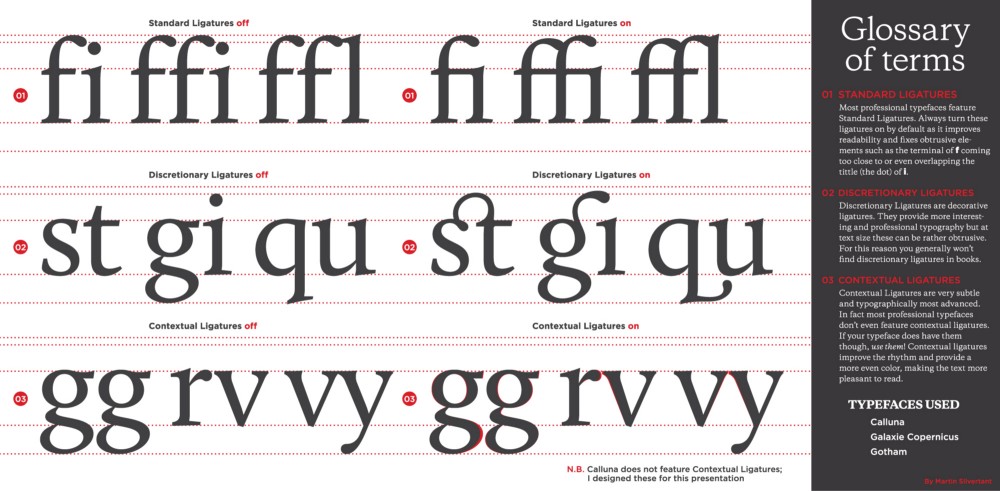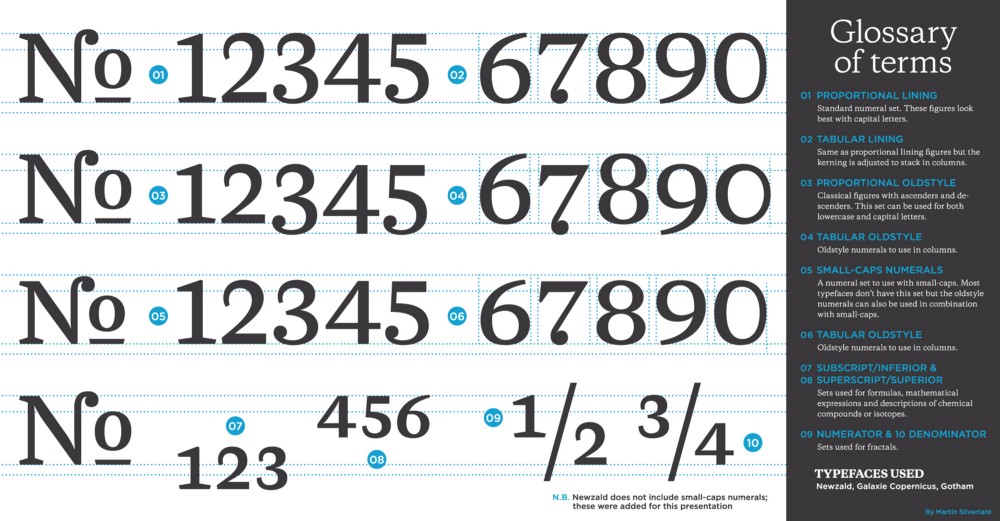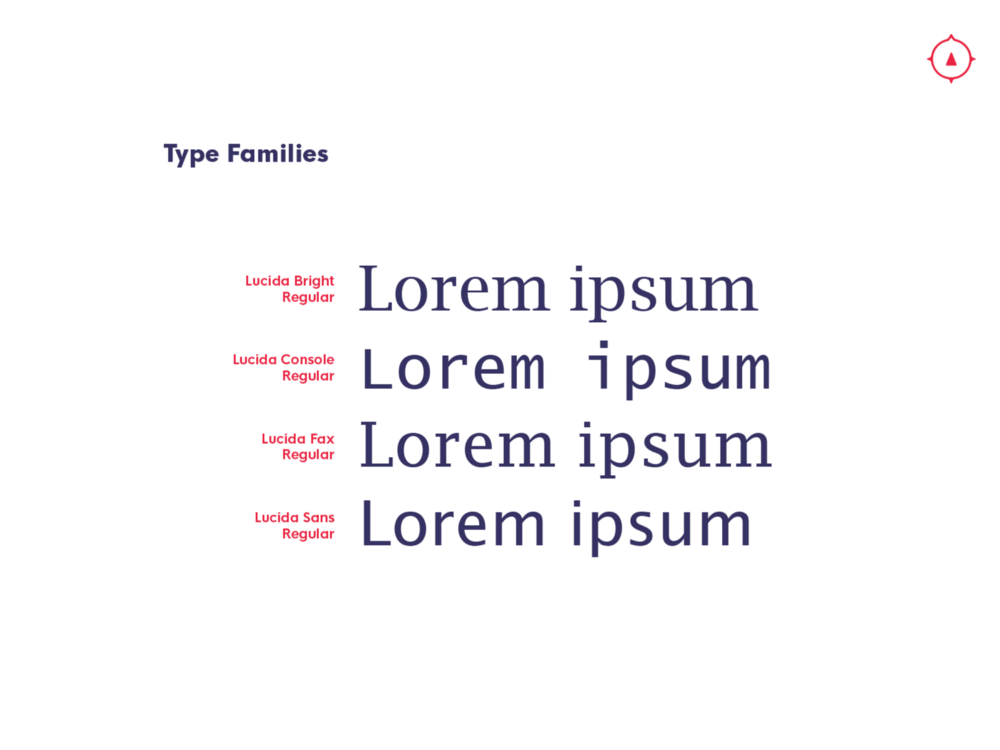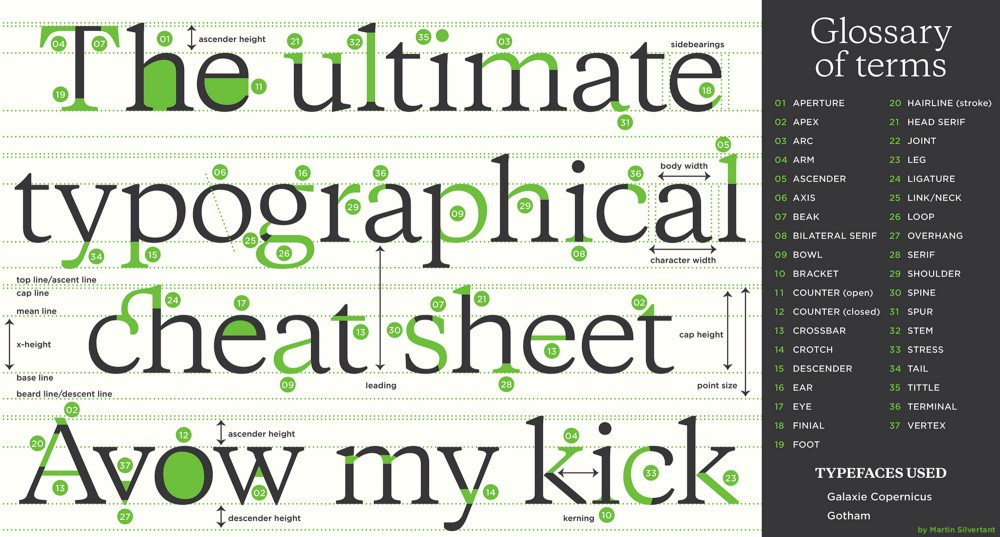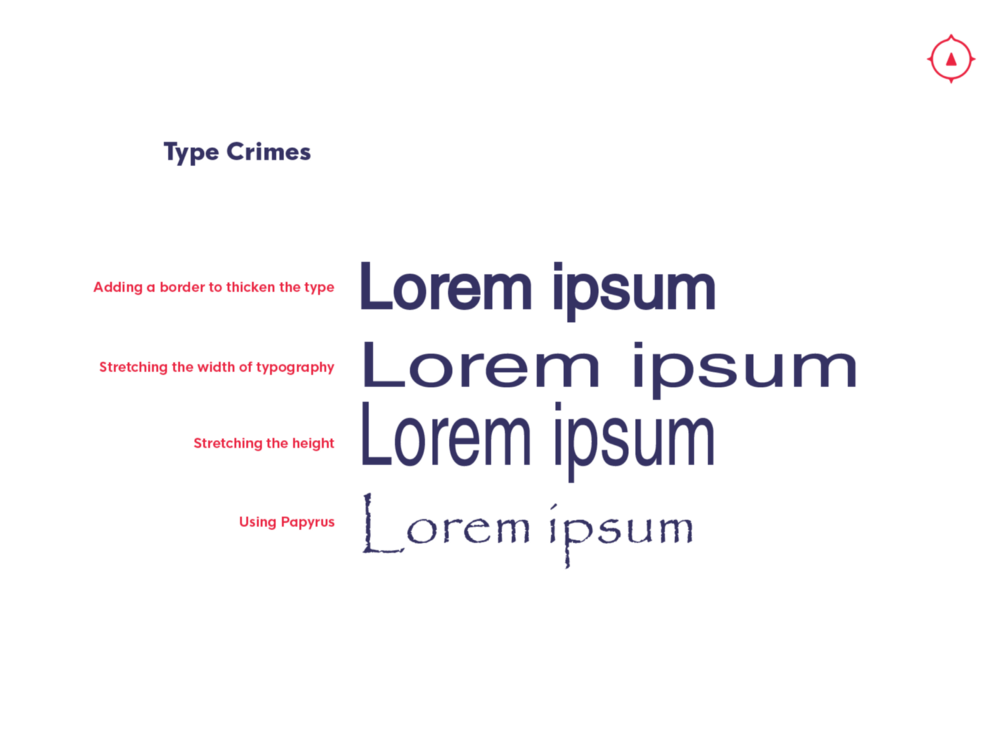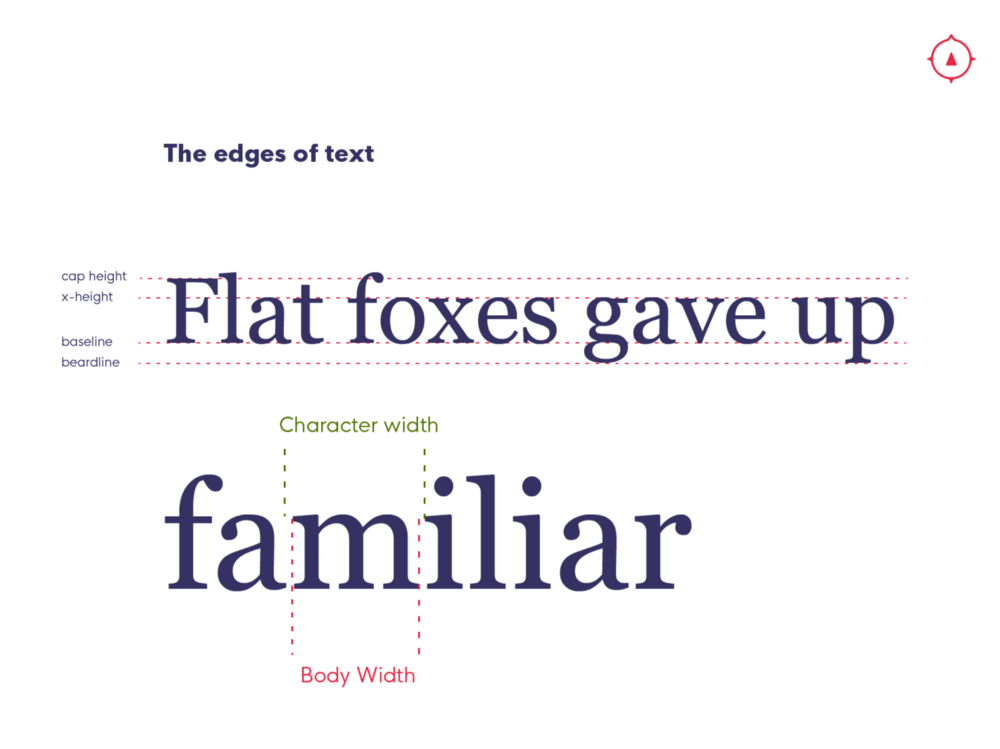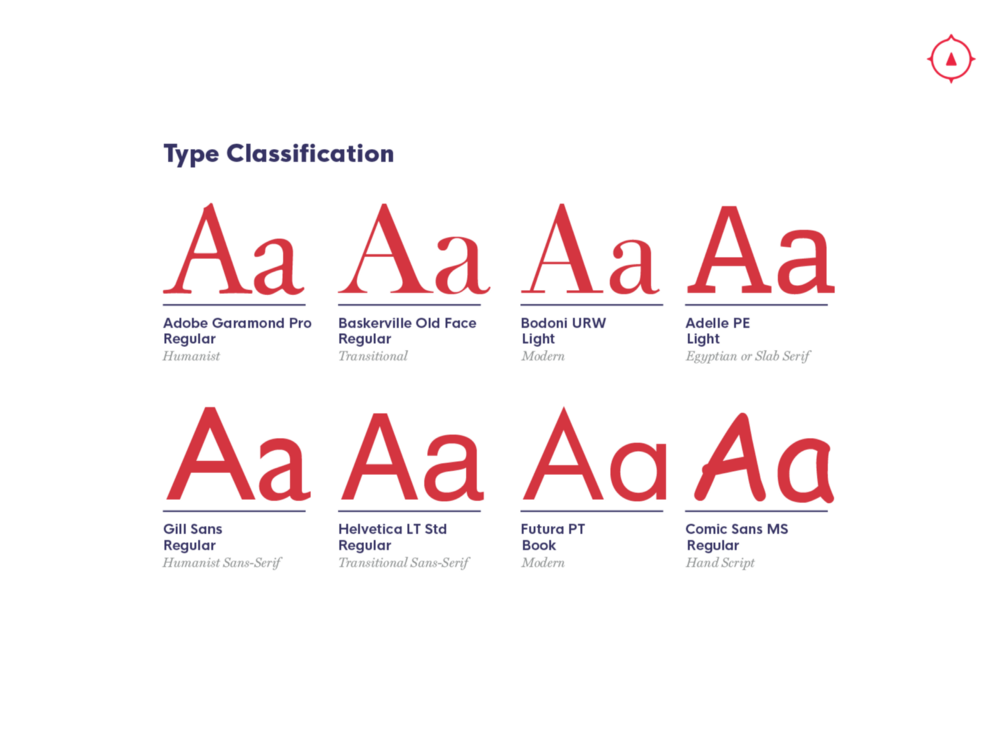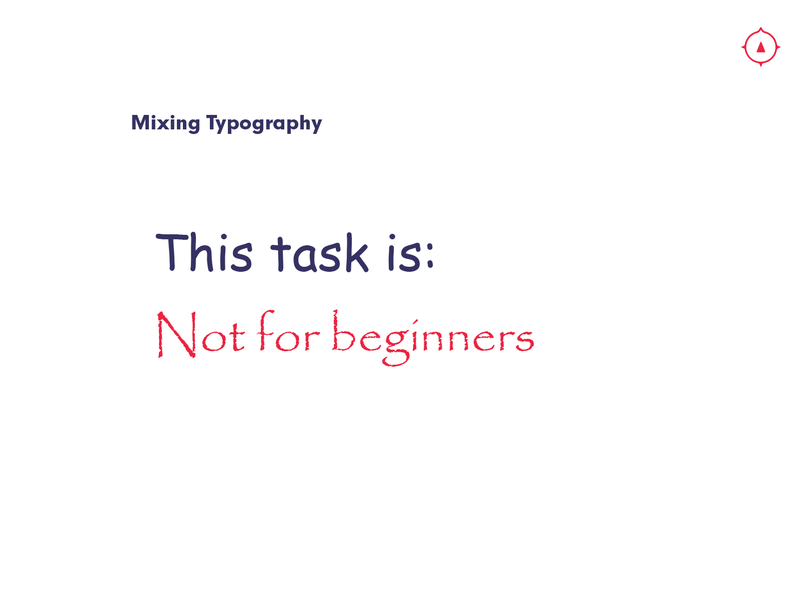
Trong phần này, chúng ta sẽ không nói tới tới bất kì một typeface cụ thể hay nên chọn font nào để dùng. Thay vào đó, ta sẽ nói về việc chọn typeface sao cho hiệu quả nhất dựa trên tính chất của chúng. Bằng cách tham khảo một số loại typeface nổi tiếng, ta sẽ hiểu được điểm mạnh cũng như tính ứng dụng của chúng trong thực tiễn.
Có bao giờ bạn nhìn vào danh sách fonts mà mình có rồi đơ mặt ra vì không biết chọn gì từ bộ sưu tập 1000 font chữ mà bạn đã kì công “tích cóp”? Có một thứ gọi là “decision fatigue” (tạm dịch: chứng mệt mỏi vì phải quyết định) sẽ làm giảm khả năng phân tích của bạn khi có quá nhiều lựa chọn. Trong thiết kế UX, việc không thể quyết định khi trước mắt có quá nhiều ngả rẽ được gọi là Luật Hick. Việc đưa ra lựa chọn luôn cần kiến thức nền tảng. Bên dưới chúng ta sẽ có dịp xem những typeface khác nhau và đặc điểm của chúng để có thể “chọn mặt gửi vàng”.
Chìa khóa để chọn type đẹp nằm ở sự tương phản. Và để tạo ra độ tương phản hợp lý, đầu tiên ta phải hiểu tương phản trong typography là như thế nào.
Typography đã có mặt từ khi chữ viết ra đời. Thậm chí những thứ chúng ta đinh ninh là “typography hiện đại” cũng đã xuất hiện từ 600 năm trước. Sự tiến hóa của công nghệ typography đã trải qua nhiều biến chuyển lớn từ chữ viết tay đến typeface kỹ thuật số trong vài thập kỉ trở lại đây. Typography được định hình qua những thời điểm cụ thể trong lịch sử, và cũng rất nhiều typeface được đặt tên theo những người trong các thời kì đó. Thông lệ này vẫn kéo dài đến ngày nay, cho nên nếu bạn thấy typeface nào có tên ngồ ngộ thì đó có thể là tên của tác giả hoặc người làm mẫu cho kiểu chữ đó. Những tiến bộ kỹ thuật trong các thời kì này ảnh hưởng rất lớn đến cách chúng ta dùng và phân loại kiểu chữ.
Serif nguyên bản (humanist serif)
Các typeface serif nguyên bản mang dáng dấp của chữ thư pháp và chữ La Mã. Trải qua thời cực thịnh vào thế kỉ XV và XVI, loại chữ kinh điển này được dựng theo chuyển động của bàn tay: Chúng có nét đi lên mảnh và nét đi xuống dày, serif và terminal (tham khảo phần Giải phẫu học type) trông tự nhiên và nét chữ rất giống chữ viết tay cổ điển.
Serif chuyển tiếp (transitional serif)
Được phổ biến bởi John Baskerville, dạng chữ này trông sắc bén hơn những phiên bản nguyên mẫu của chúng. Bằng sự tiến bộ của kỹ thuật in, chúng ta đã có thể tạo ra những nét mỏng hoặc dày hơn. Loại chữ này được dùng để thay thế serif nguyên bản nhưng thật ra ngày nay chúng ta chỉ có thể thấy chúng trong sách và văn bản cũ. Serif font hiện đã lỗi thời, nhưng vẫn chưa hoàn toàn biến mất.
Serif hiện đại (modern serif)
Typography hiện đại và tân cổ điển tiếp tục đẩy mạnh sự tương phản giữa nét mỏng và nét dày trong kiểu dáng chữ. Ban đầu, đây chỉ được xem là bước chuyển đổi tạm thời nhưng dần dần, với hình thái ngày càng thẳng thớm và có độ tương phản cao, serif hiện đại đã trở thành một phân nhánh riêng.
Lúc bấy giờ, mọi người đã rất phản đối kiểu chữ này. Nghĩ cũng thấy lạ, tôi không ngờ rằng cả đám đông lại có thể phản ứng gay gắt thế đối với một thiết kế…
Serif Ai Cập và Serif phiến (Egyption serif, slab serif)
Từ những mẫu quảng cáo truyền thống, chúng ta đã bắt đầu ứng dụng những kiểu chữ serif dày hơn; trông chúng chả khác gì kiểu chữ sans-serif nhưng có thêm phần serif rất dày. Độ dày phần serif biến đổi đa dạng giữa các typeface, từ hình thái dày dặn đồng đều cho tới lúc nặng lúc thanh. Nhưng dù ở dạng nào đi nữa, chúng hay được sử dụng cho phần header bởi đặc tính vô cùng bắt mắt.
Sans-serif nguyên bản (humanist sans-serif)
Kiểu chữ sans-serif nguyên bản được dùng chủ yếu vào đầu thế kỉ XX, giữ lại nhiều tính chất của kiểu chữ serif cơ bản trong đó có độ dày của nét. Bằng một lí do kì quái nào đó, mọi người lại phẫn nộ với kiểu chữ này. Serif được cho rằng khá nặng nề và làm khoảng cách giữa các kí tự rối ren. Chúng ta tạo ra những kiểu chữ không có serif để tăng legibility (tính dễ đọc của chữ), nhưng rốt cuộc chúng lại thay đổi cách nhìn nhận của chúng ta.
Sans-Serif chuyển tiếp (transitional sans-serif)
Kiểu chữ sans-serif chuyển tiếp là một trong những loại chữ phổ biến nhất. Nếu bạn đã từng nghe Helvetica, thì bạn đã tiếp xúc với kiểu chữ này rồi đấy, chúng có dáng thẳng và rõ ràng. Bạn có thể để ý thêm rằng độ dày giữa các kí tự vô cùng đồng nhất. Kiểu chữ nào cũng “màu mè” một tí nhưng sans-serif thì vẫn mộc mạc xuyên suốt các thời kì.
Sans-serif hình học (geometric san-serif)
Kiểu chữ này cũng khởi nguồn từ thế kỉ XX khi những chữ cái được dựng nên từ hình học. Trông chúng rất sắc sảo và đồng đều nên có thể tạo ra cảm giác tương phản cao khi đi cùng với loại typeface khác.
Chữ viết tay
Cái tên tự miêu tả. Đây là chữ viết tay được chuyển về dạng kỹ thuật số. Chúng cho cảm giác được nắn nót bởi bàn tay người trong thời đại mà typography hầu hết được tạo nên từ máy móc.
Để lựa chọn các typeface theo đúng mục đích, bạn cần có thêm kiến thức về đường gióng. Có 4 loại đường gióng chúng ta cần xem xét:
Ngoài ra, bạn có thể tham khảo thêm cuốn Suy nghĩ bằng chữ (Thinking with type). Đây là cuốn sách đã khơi gợi cảm hứng cho mọi thứ tôi chia sẻ và cũng bàn luận rất chuyên sâu về những kiến thức cần thiết và ngoài ra, còn có phần hướng dẫn cách sử dụng grid tuyệt vời nhất mà tôi từng đọc. Tôi hy vọng là bài viết này đã giúp cho bạn có cái nhìn khách quan về type. Nếu bạn có bất cứ câu hỏi nào, đừng ngần ngại liên hệ với tôi.